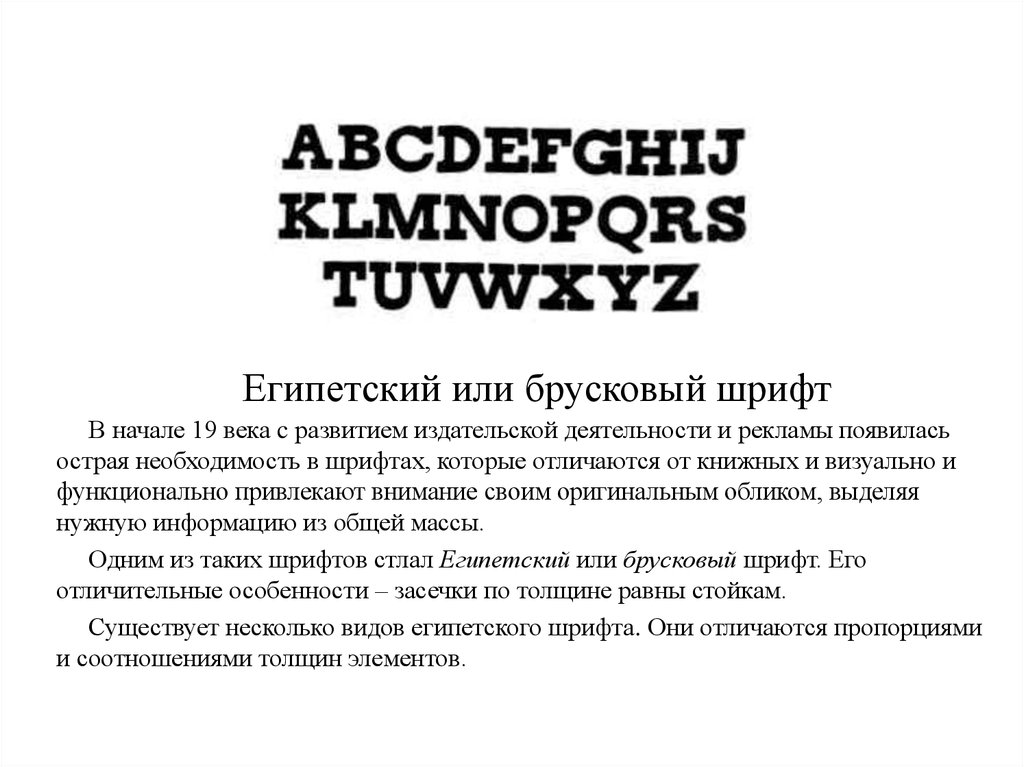
Брусковая Антиква: секреты применения и стили
Брусковая Антиква — классический шрифт, который подходит для создания стильного и элегантного дизайна. В нашей подборке вы найдете вдохновляющие примеры использования и полезные советы для работы с этим шрифтом.
Используйте шрифт Брусковая Антиква для заголовков, чтобы придать тексту выразительность.
Сочетайте Брусковую Антикву с простыми шрифтами, чтобы подчеркнуть ее уникальность.
Выбирайте мягкие цвета для текста, чтобы усилить классический вид шрифта.
Используйте Брусковую Антикву в проектах с исторической или винтажной тематикой.
Регулируйте межбуквенное расстояние, чтобы текст выглядел аккуратнее.
Не используйте слишком мелкий размер шрифта — Антиква лучше смотрится в крупных заголовках.
Применяйте Брусковую Антикву для оформления печатных изданий, таких как книги и журналы.
Избегайте использования слишком яркого фона, чтобы сохранить читаемость текста.
Добавляйте легкие декоративные элементы, чтобы подчеркнуть стиль шрифта.
Экспериментируйте с прозрачностью текста для создания необычных эффектов.